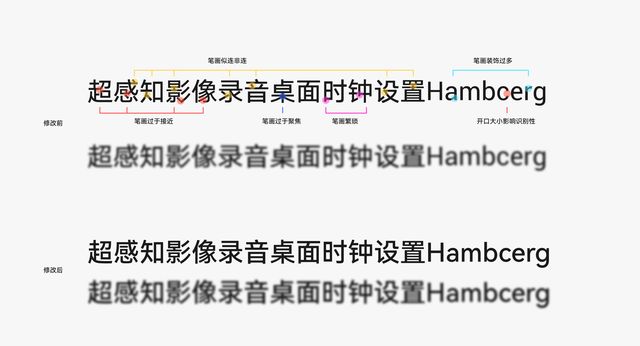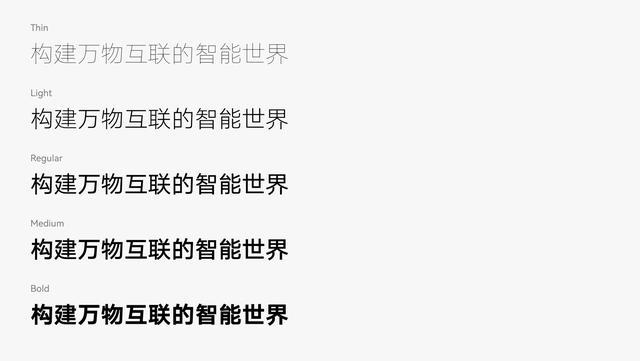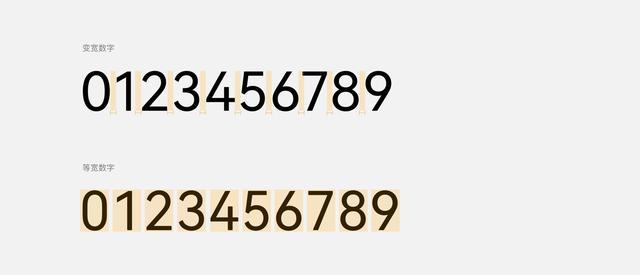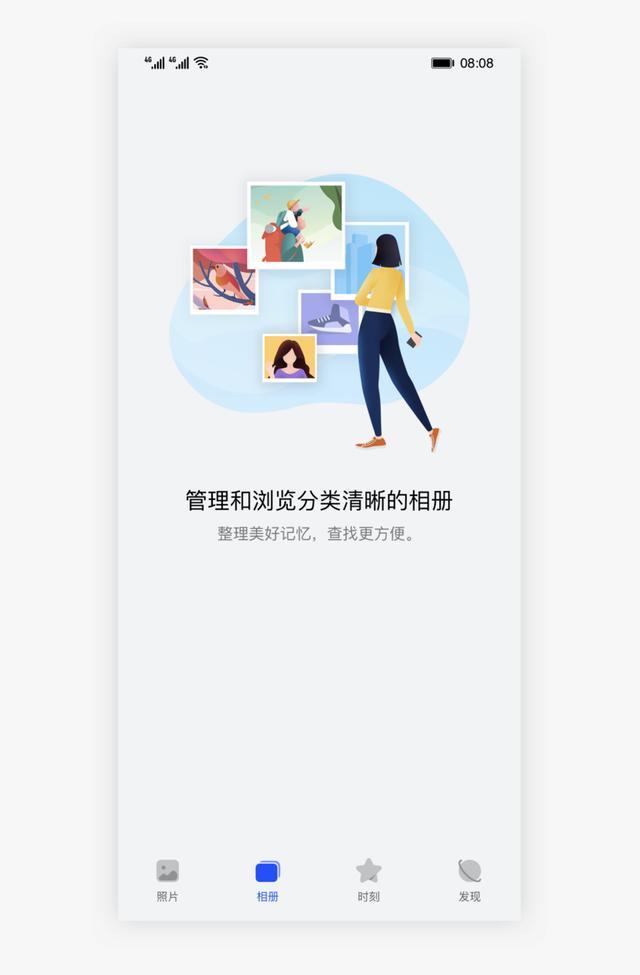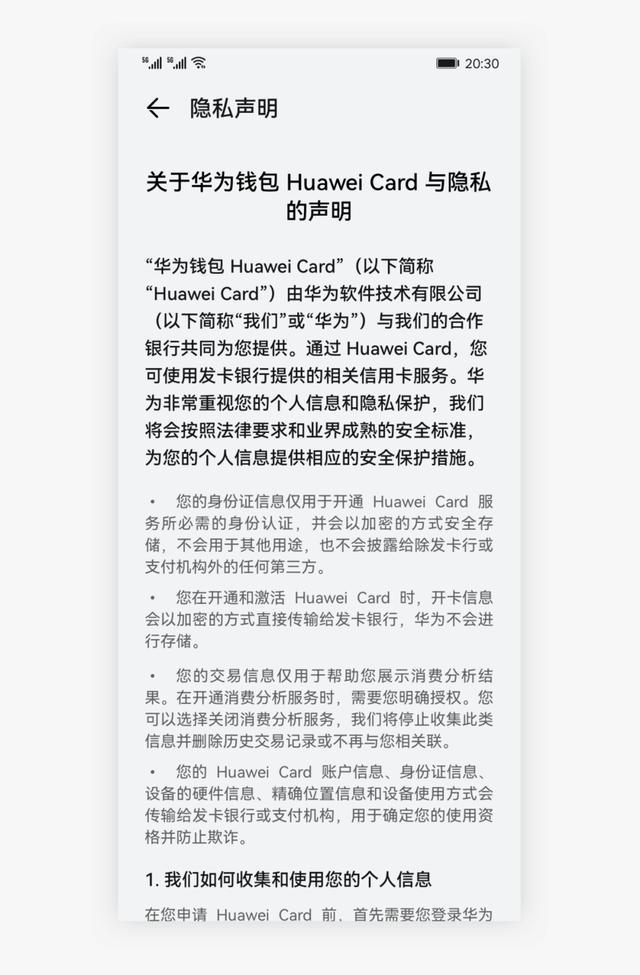
IT之家 6 月 27 日消息 今年 6 月,华为正式推出了鸿蒙 HarmonyOS 2,同时还发了一款全新品牌定制字体 HarmonyOS Sans,可免费商用,主要特点是优化字体灰度,统一多语言字形风格等,官方现已提供下载。
华为表示,通过研究用户在不同场景下对多终端设备的阅读反馈,综合考量不同设备的尺寸、使用场景等因素,综合考虑用户使用设备时因视距、视角的差异带来的字体大小和字重的不同诉求设计出来这一字体。
IT之家曾报道,HarmonyOS Sans 由汉仪字库字体设计团队制作,聚焦于万物互联的功能性和普适性,是一款多语言的无级可变字体,使多语言下阅读体验更加一致。
据悉,该字体支持包含简繁中文、拉丁、西里尔、希腊、阿拉伯等 5 大书写系统,支持 105 种语言全球化覆盖,助力构建万物互联的智能世界。
官方介绍称,在保障字体体验的功能性前提下,华为 HarmonyOS Sans 在人文和现代中找到新的平衡。在短笔画时保持横平竖直,简约无装饰,在撇捺弯钩长笔画中融入书法的笔势美学,优化字体灰度,提升阅读体验。
HarmonyOS 字体特性
动态字重粗细调节,支持可变特性,让用户选择他们喜欢的字体粗细来进行文本的显示。
支持更多字重能力:增加了 Thin、Light、Bold、Black 的字重能力。
支持变宽和等宽两种样式。
支持时钟字体特性,冒号格式会根据时间格式自动调整位置。
字体排版
多设备字号层级
文本对齐规则
▲居中对齐可以更容易获得用户的注意力